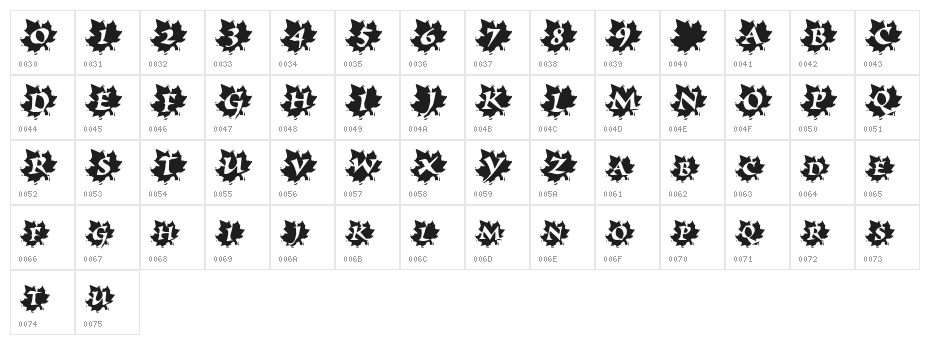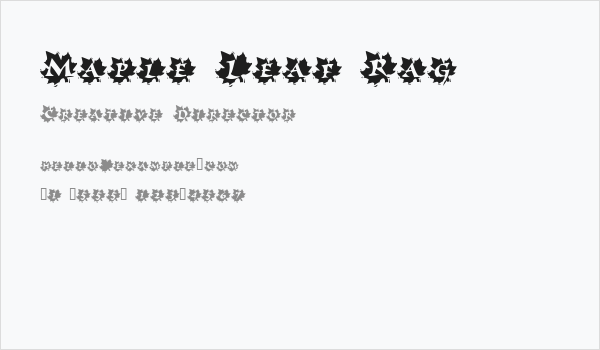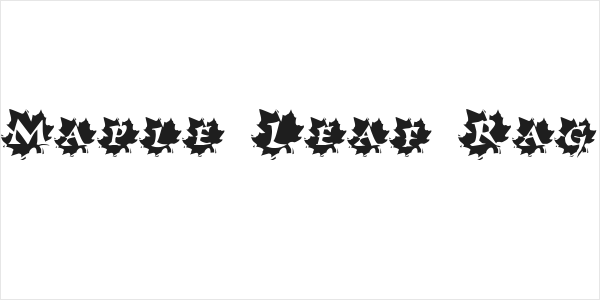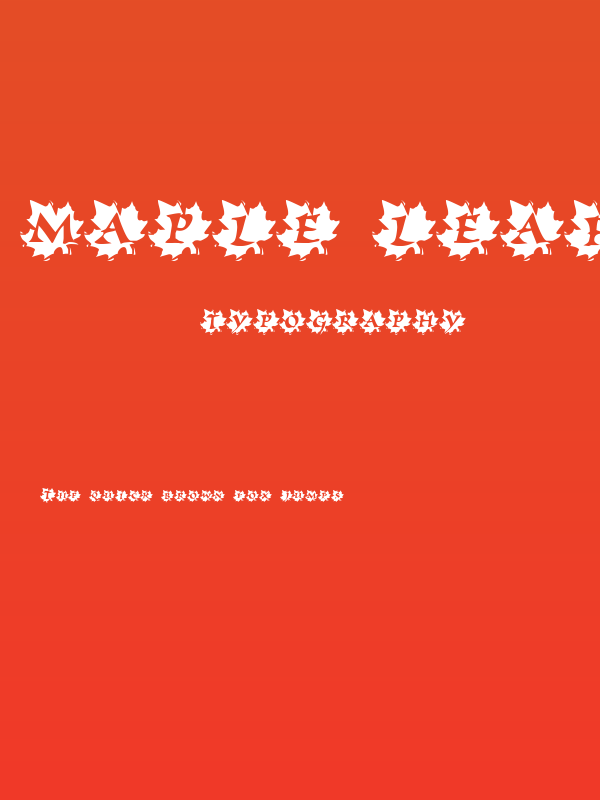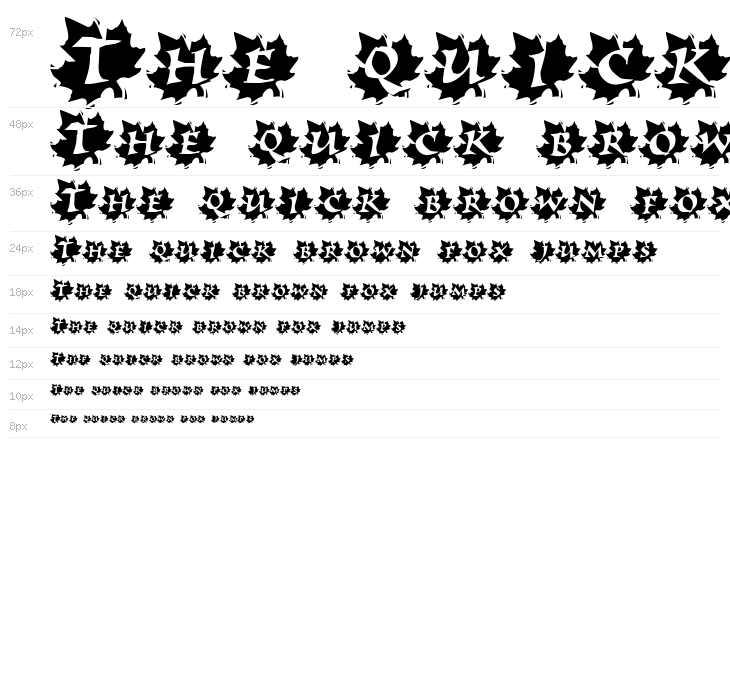
Maple Leaf Rag Font
| おすすめプロジェクト | Ideal for nature-themed designs, autumn festival posters, eco-friendly brand logos, and playful children's book covers. |